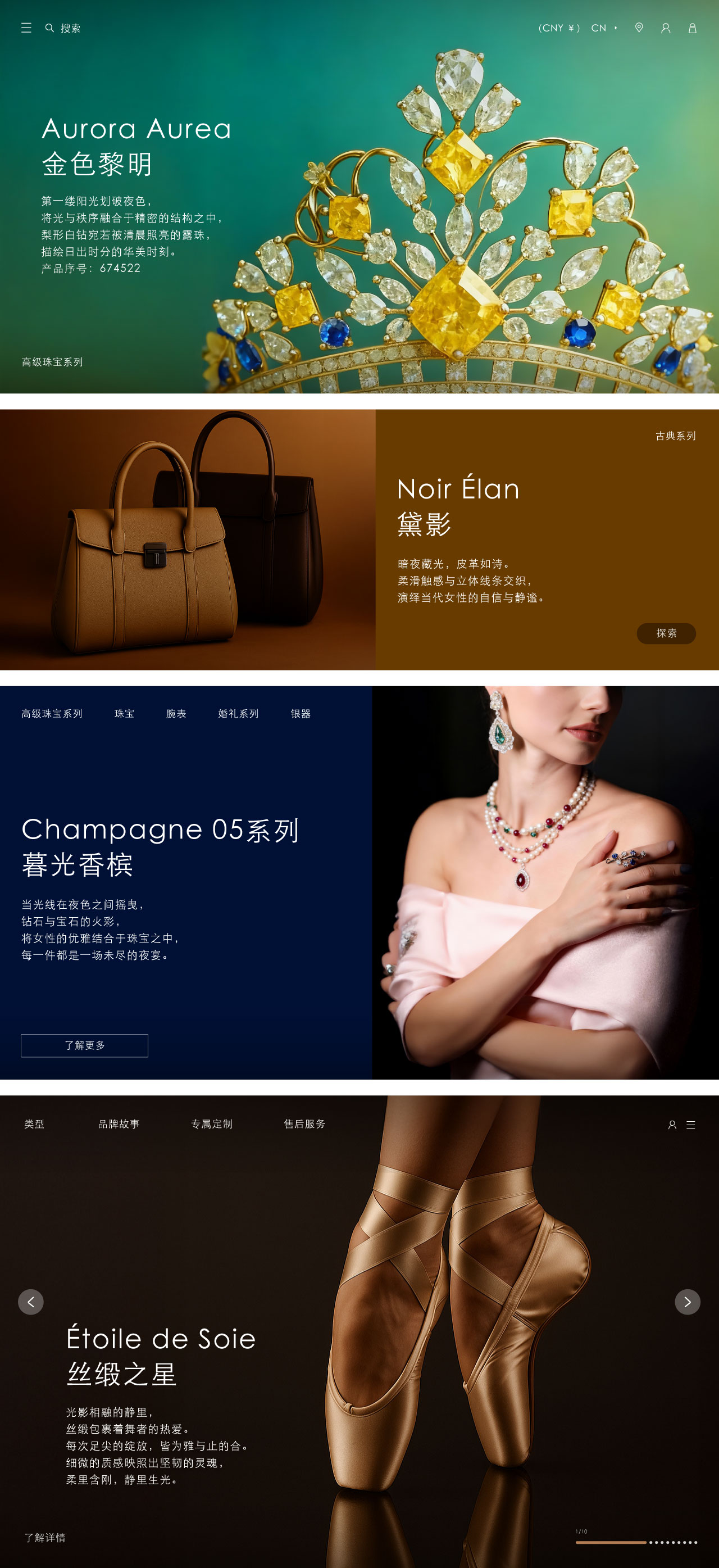
华文细黑 / STXihei / Light
华文细黑
在有限的空间进行无限分割
华文细黑 / STXihei
设计师:
常州华文
字体介绍:
华文黑体字体是一款非常端正的中文字体,大方得体,华文黑体承袭了国家於六十年代、委托上海印刷研究所和字模厂的老师傅设计的黑一体、黑二体的模样,字体受传统中国书法美学的影响,结构外弛内张,构成的字体感觉传统儒雅,而且充满人性,比起新派设计-负空间讲究平均分布的,在以汉字为主的文字上可读性要胜一筹。